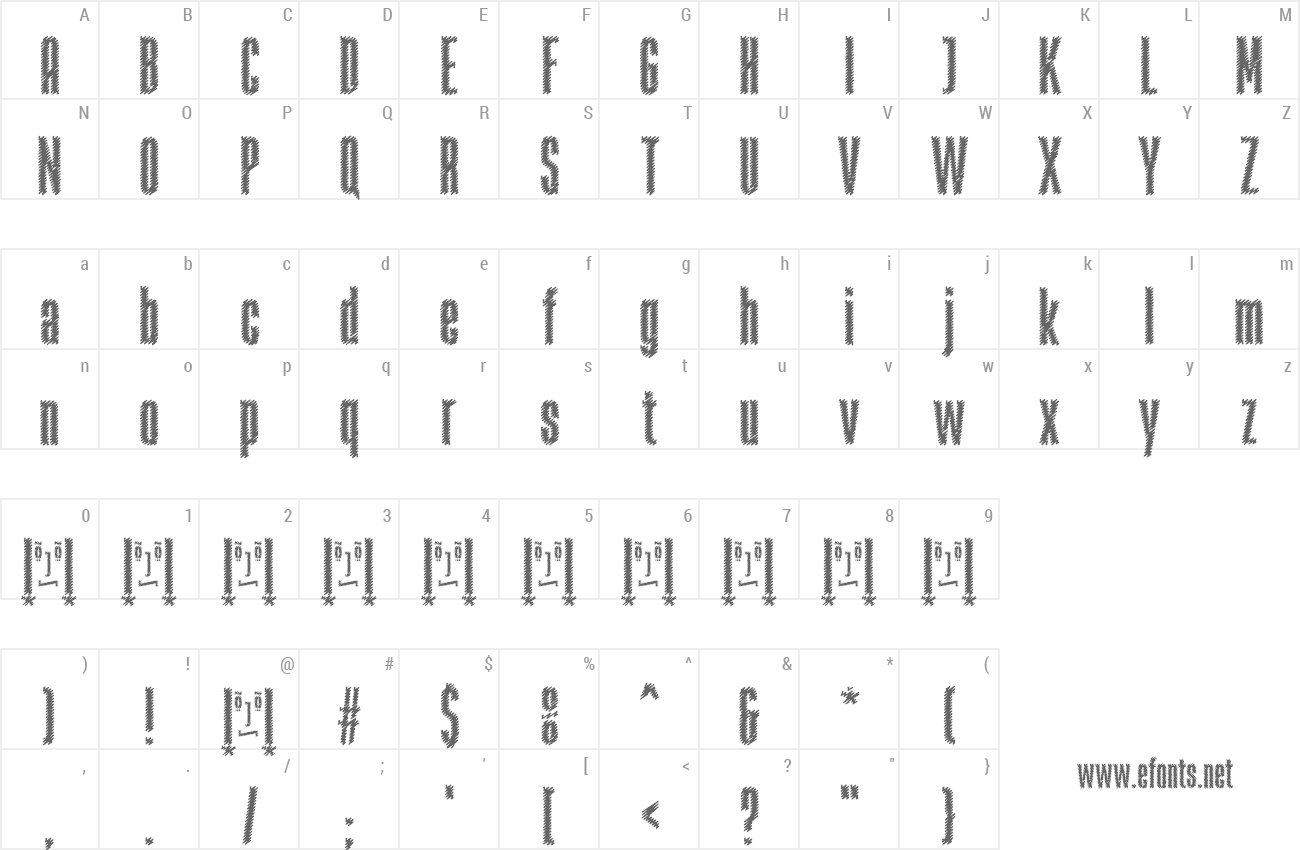
| Font name: | Rabiosa |
| Author: | deFharo |
| Note by deFharo | |
Tipografía simpática, garabateada y nerviosa. Fuente display & condensada para diseños de grandes títulos en carteles, afiches o publicidad en general. Sympathetic, scribbled and nervous typography. Font display & condensed for designs of great titles on billboards, posters or advertising in general. ==================== • Descarga gratis la versión con números desde mi web, sólo para uso personal. • Licencia comercial disponible: 560 glyphs + funciones Open type + Letras griegas + letras alternativas • Download the version with numbers from my web, only for personal use only. • Commercial license available: 560 glyphs + Open type functions + Greek letters + Alternate characters: http://defharo.com/fonts/rabiosa-font/ ==================== |